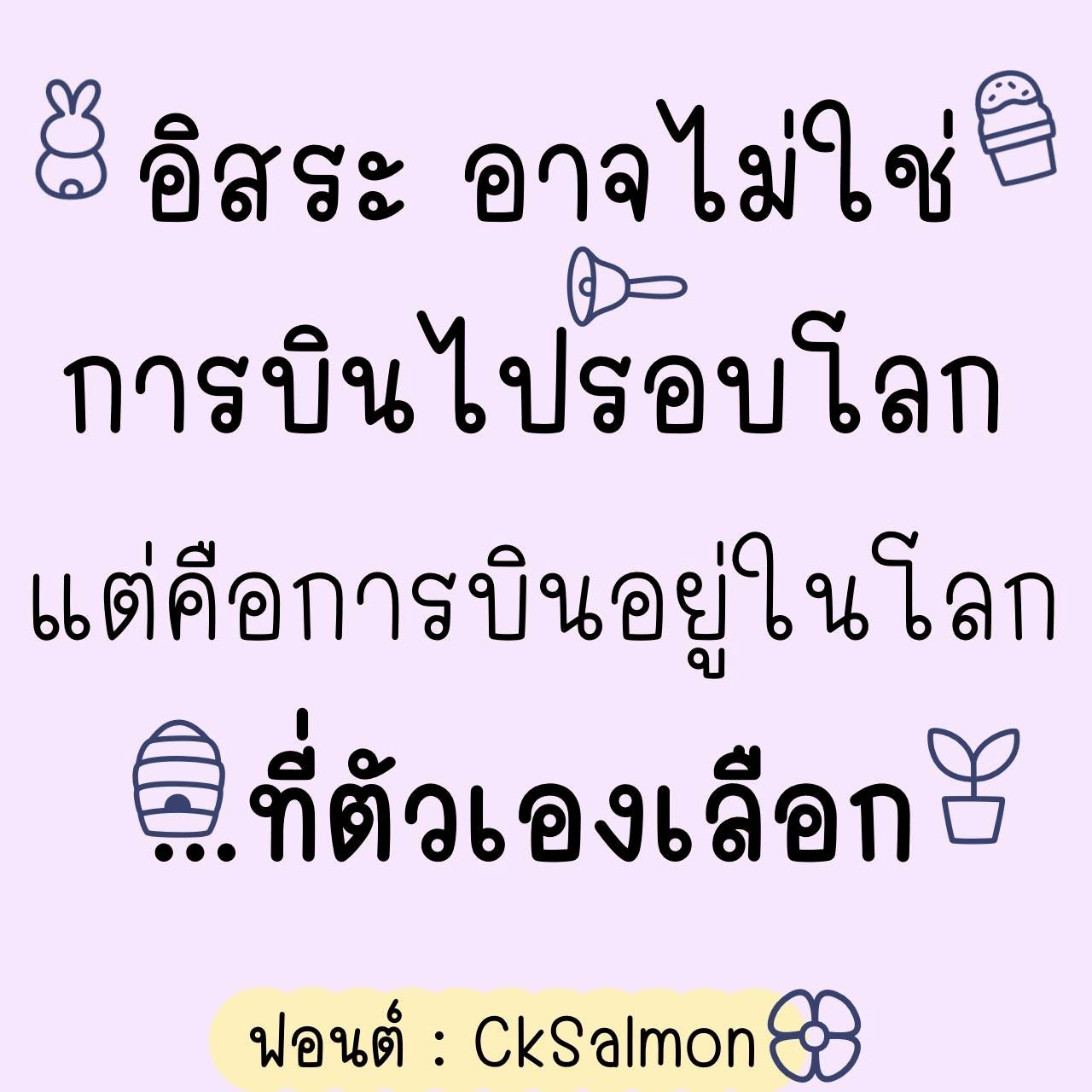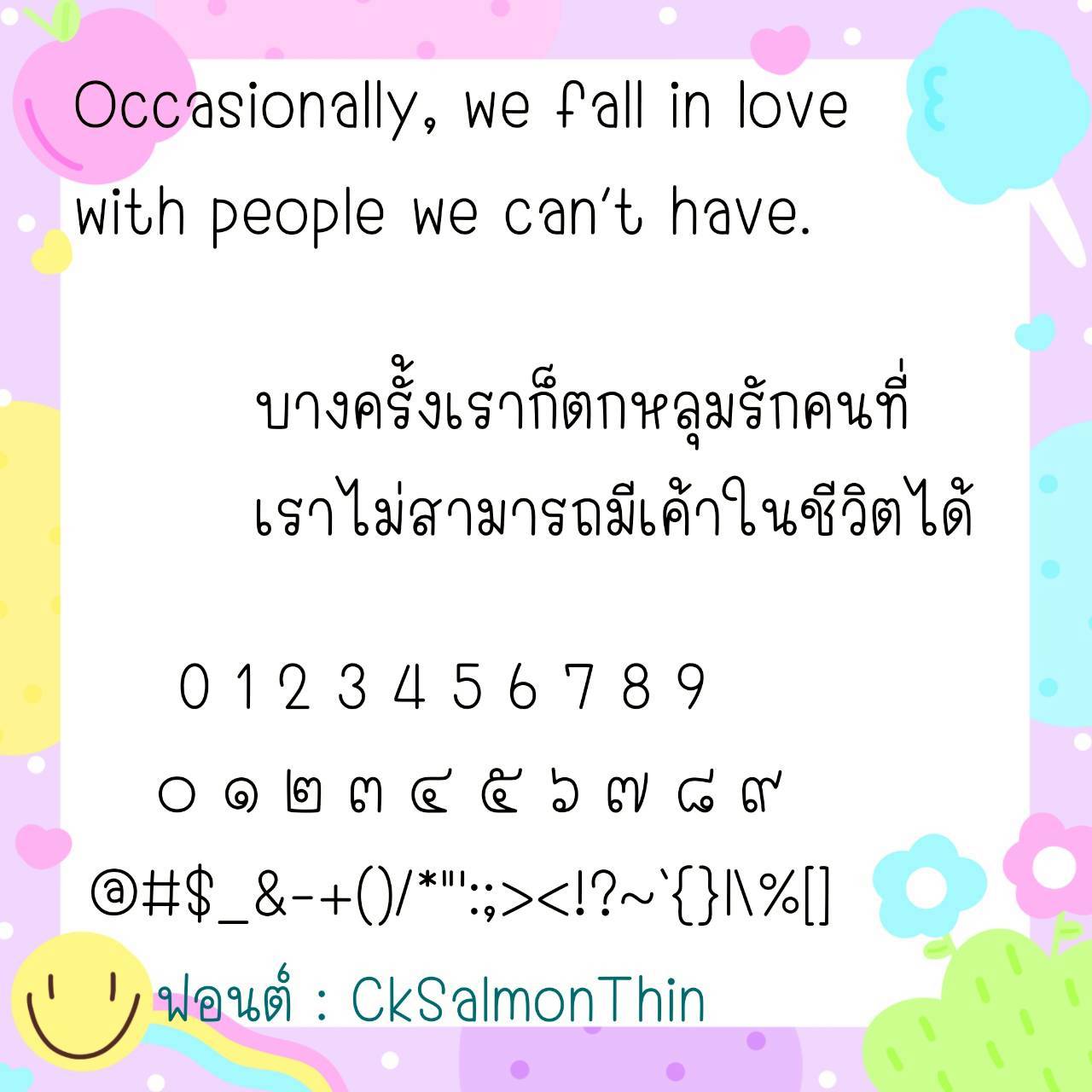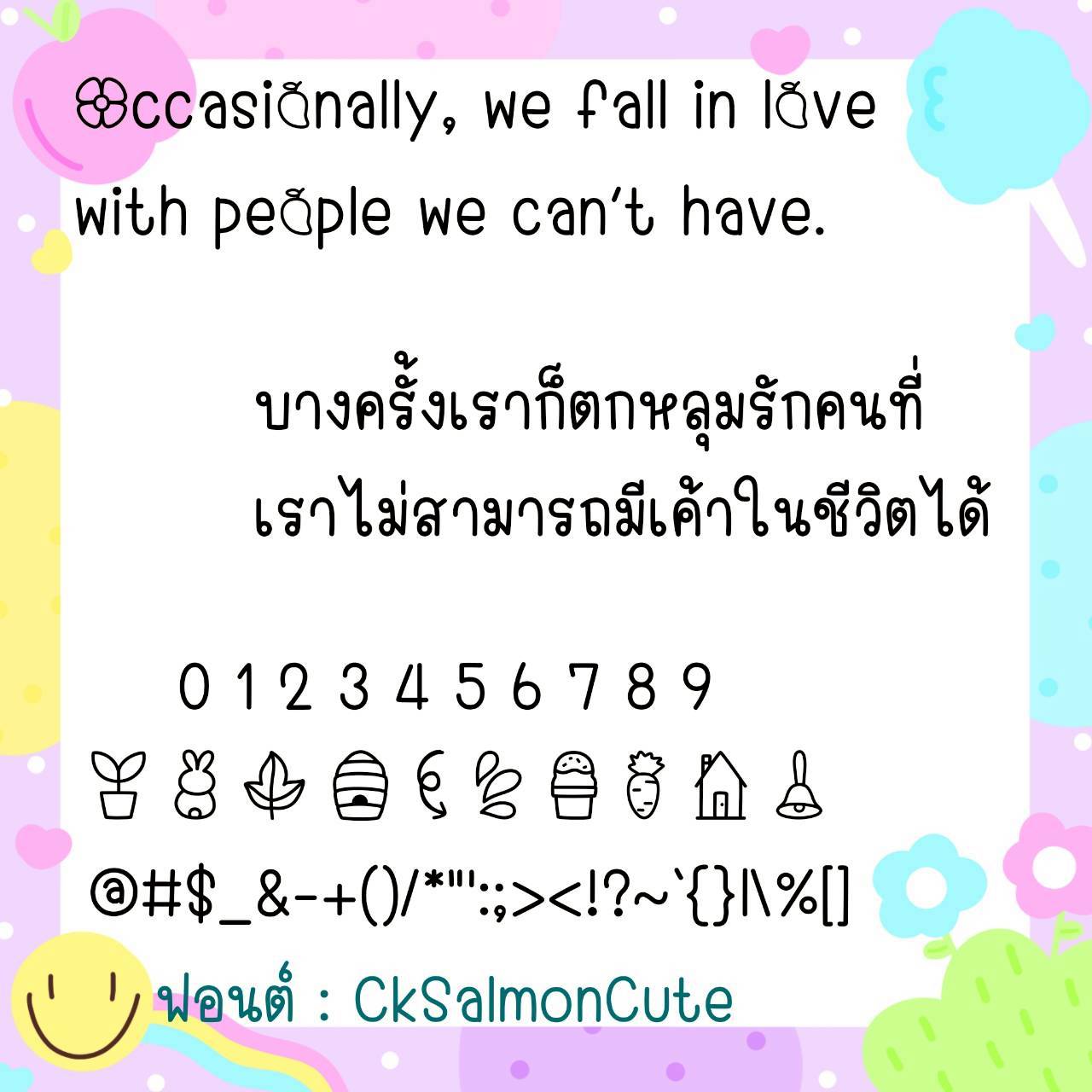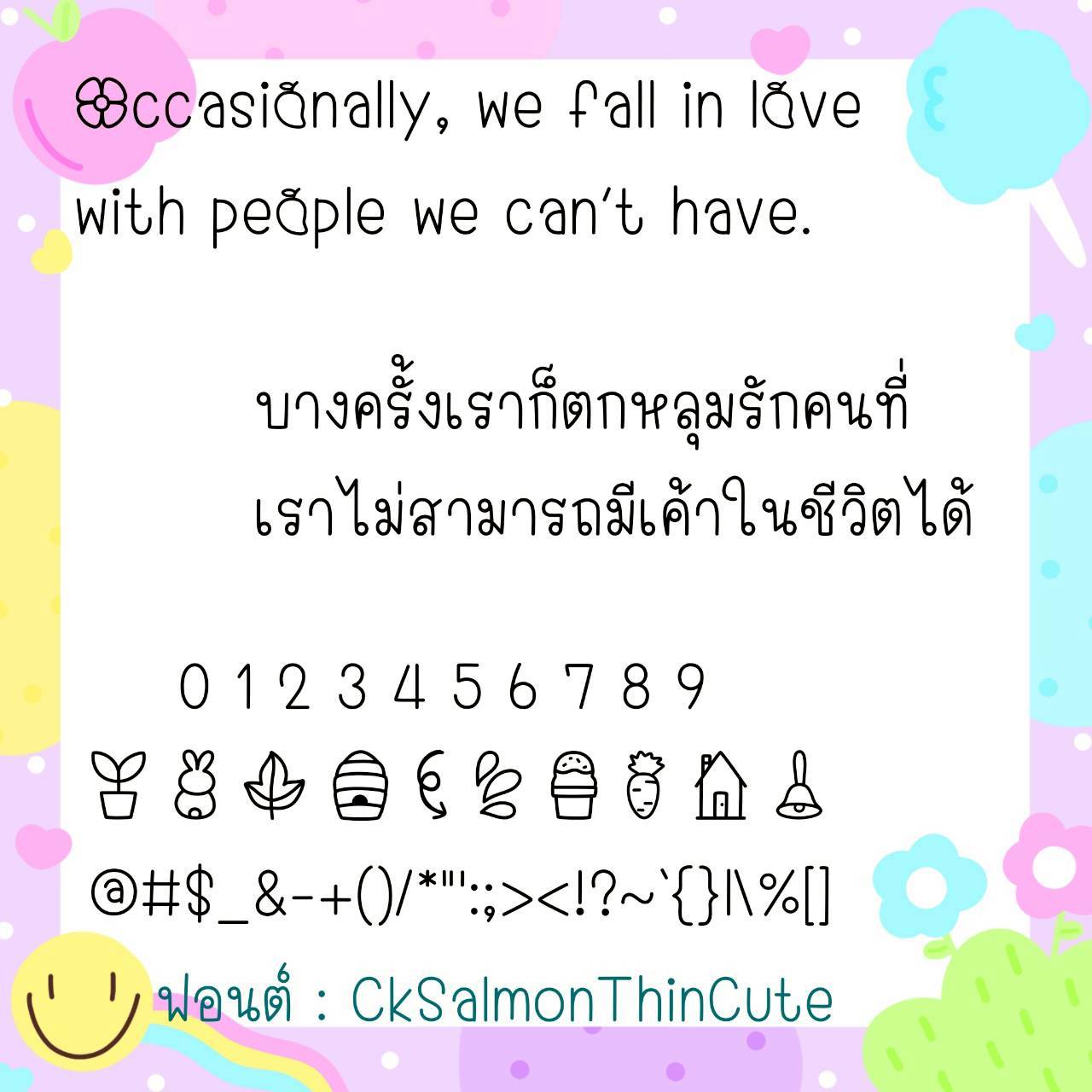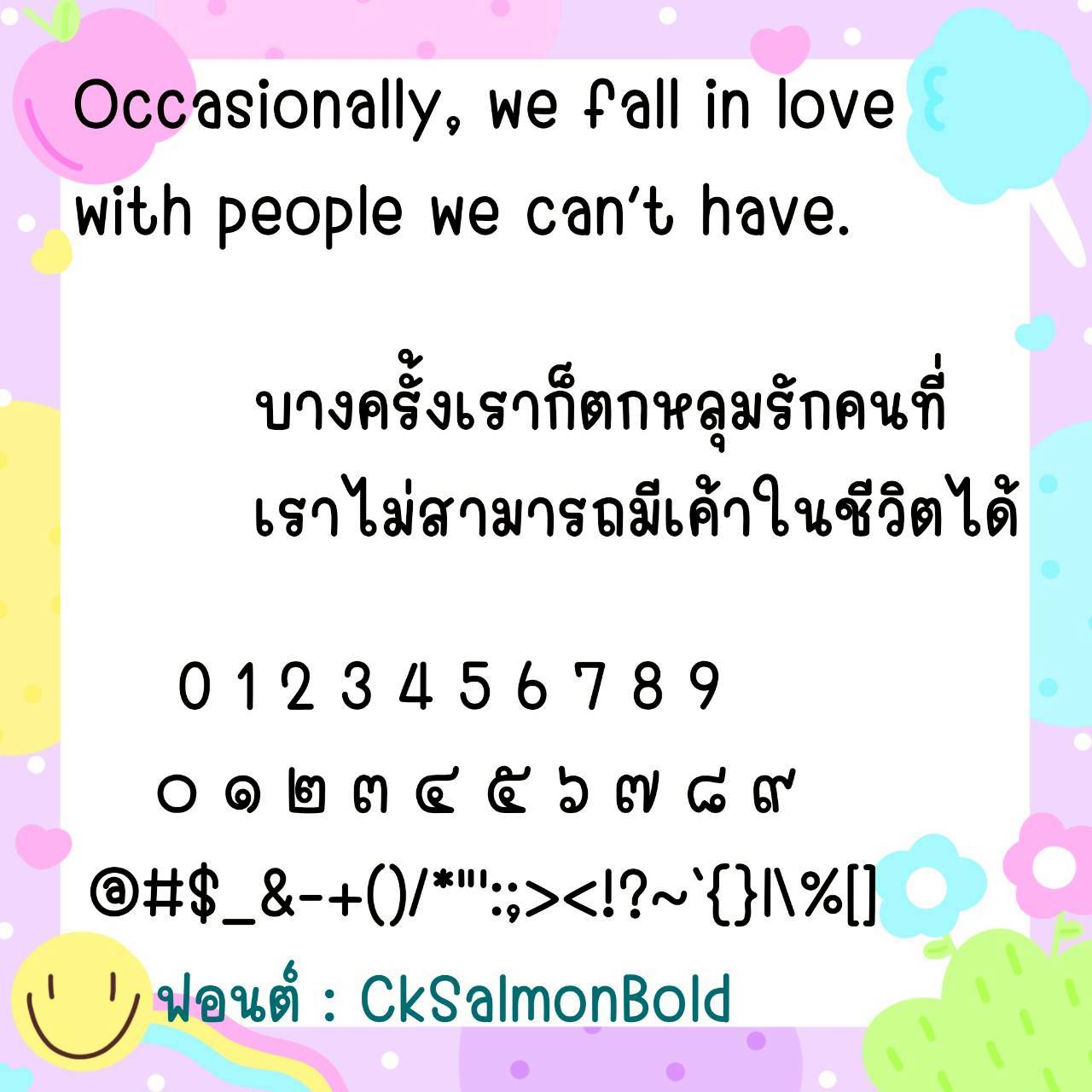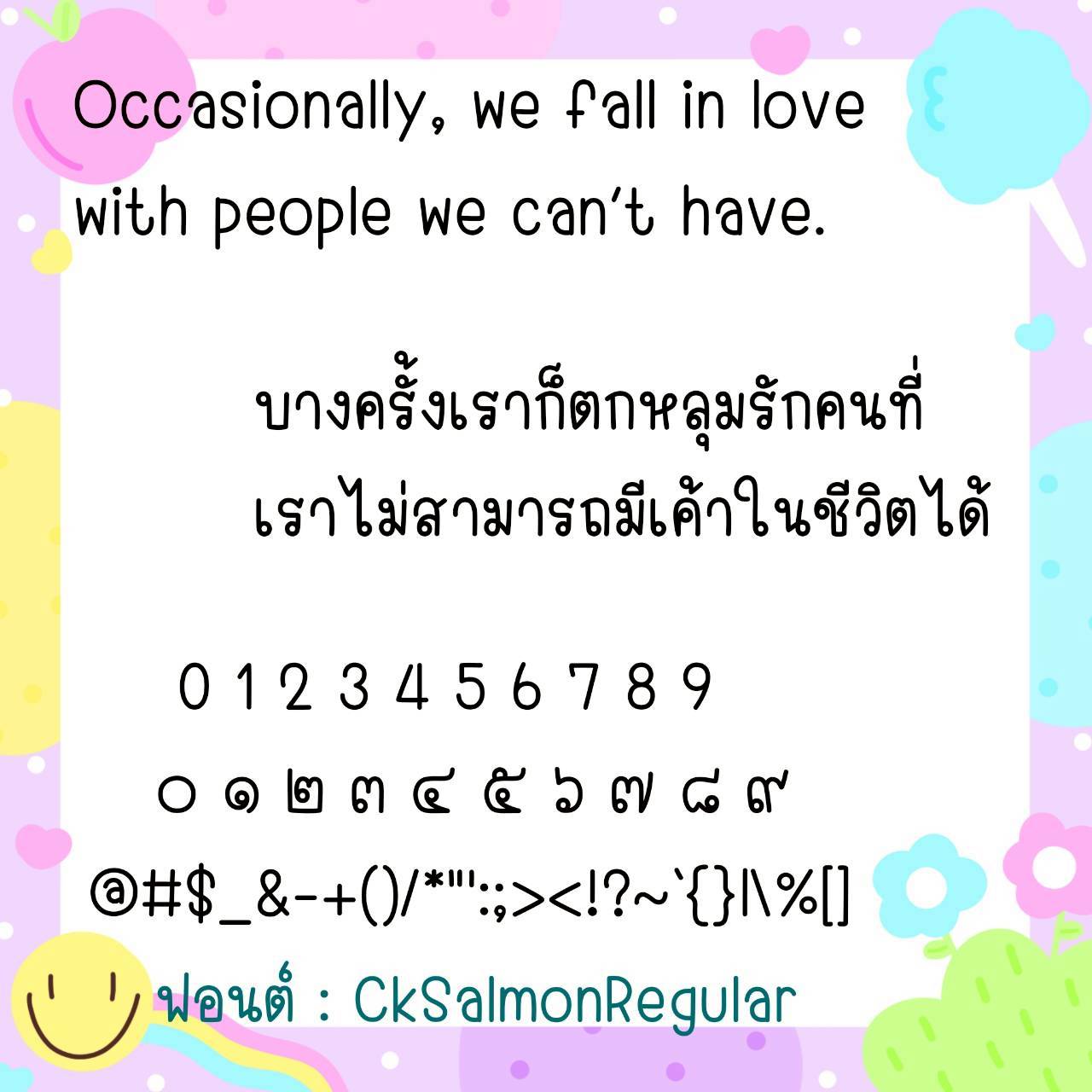
Font CkSalmon
ชื่อสินค้า : Font CkSalmon 💙
🔸 ฟอนต์ลายมือแนวตัวเล็กค่อนข้างไปทางผอม มีความน่ารักตามสไตล์วัยรุ่น แต่ยังอ่านง่ายดูไม่น่าเบื่อ และยังมีไฟล์อิโมจิน่ารักๆที่ใช้แทนเลขไทยให้ด้วยค่ะ 🥰💙
🔹 This handwritten font is small and rather thin, with a cute, youthful style, yet still easy to read and not boring. It also includes cute emoji files that can be used to replace Thai numerals. 🥰💙